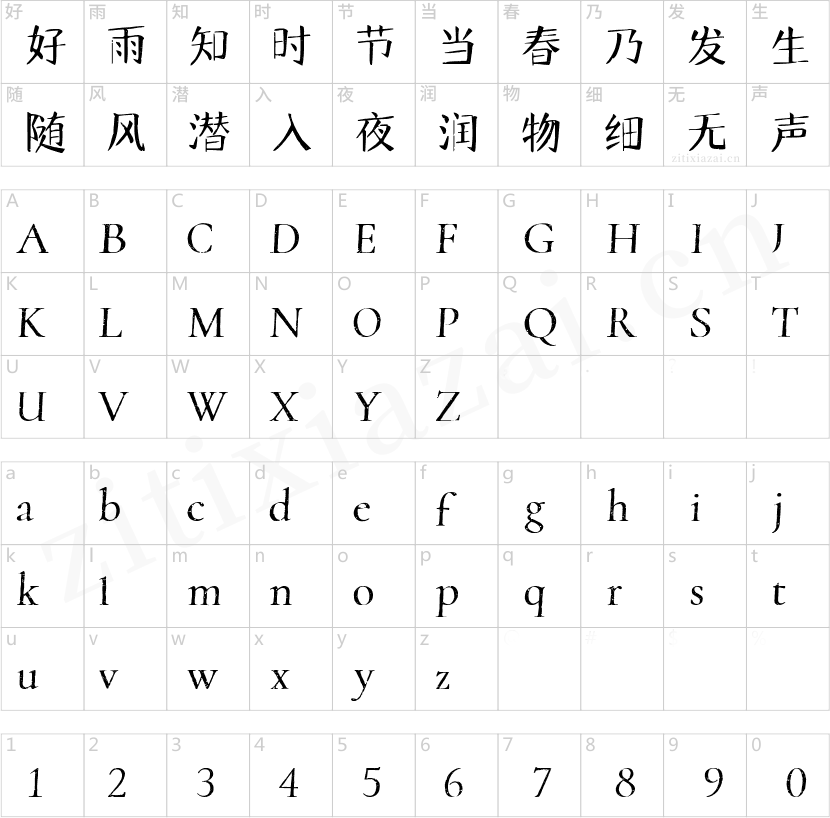
字魂193号-文宋复古体
字魂193号-文宋复古体,这款字体结构工整、笔画清晰,兼顾美观与易读性,适用于标题、正文、海报、包装、LOGO 等多种场景。字形优雅稳定,风格百搭耐看,适配日常排版与创意设计,让文字呈现更舒适、更具质感。字魂193号-文宋复古体一笔一画,皆是细节,以均衡的比例、流畅的线条打造舒适视觉体验,字形端正大气,风格简约现代。无论是商业设计、品牌宣传还是日常排版,都能轻松驾驭,让文字更有格调与力量。字魂193号-文宋复古体字体下载。
字魂字体字小魂文宋复古体字体是由字魂创意字库设计并生产的一款可商用的字体,被收录于字小魂系列。该字体支持GB-2312标准,包含6764个中文、字母、符号和数字,字体类型偏向宋体,具有中国风、简约、时尚的风格,在市面上广泛用于广告电商、社交、企业文化等场景。